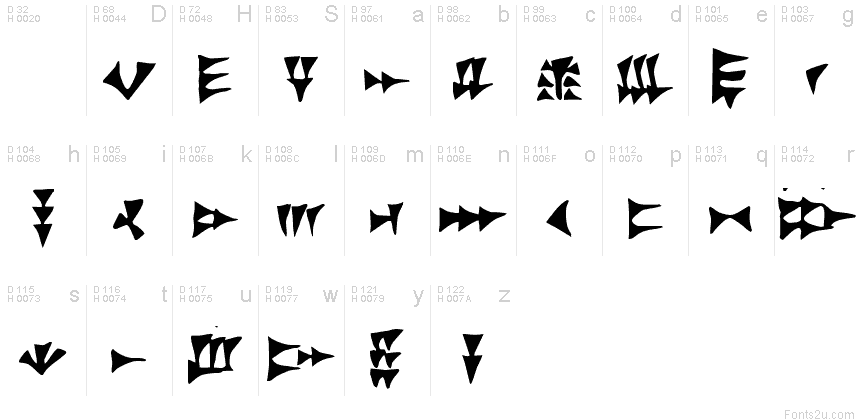
Ugarit, der kostenlose Keilschrift-Dingbat-Font von David F. Nalle, verwandelt keilförmige Zeichen in eine markante archäologische Textur. Die Symbole wirken eher wie eingemeißelt oder eingedrückt als gezeichnet – mit scharfen dreieckigen Schnitten, unregelmäßigen Verbindungen und einem trockenen, tafelnartigen Rhythmus, der sofort an antike Keilschrift erinnert.
Dieser kostenlose Font eignet sich hervorragend für Museumsgrafiken, historische Buchcover, Lore-Seiten in Spielen, Ausstellungstafeln und Titelkarten, die einen altorientalischen Bezug benötigen, ohne in Fantasy-Kalligrafie abzudriften. Er funktioniert auch gut für kurze Trenner, Kapitelanfänge und emblematische Elemente, da die massiven, fragmentierten Silhouetten eher wie archäologische Fundstücke wirken als wie gewöhnliche Ornamente.